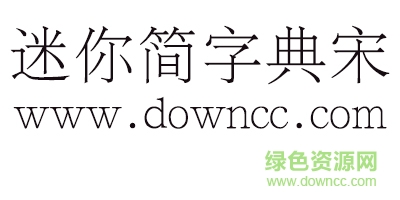
迷你簡字典宋字體是一款迷你字體設(shè)計方面的字體,能夠讓你的輸入法字體擁有超強(qiáng)的個性化。
宋體,是為適應(yīng)印刷術(shù)而出現(xiàn)的一種漢字字體。筆畫有粗細(xì)變化,而且一般是橫細(xì)豎粗,末端有裝飾部分(即「字腳」或「襯線」),點(diǎn)、撇、捺、鉤等筆畫有尖端,屬于襯線字體(serif),常用于書籍、雜志、報紙印刷的正文排版。
宋朝文化興盛,印刷業(yè)有了巨大發(fā)展,從南宋時期,在臨安等地的印刷作坊里就開始出現(xiàn)了類似印刷體的字體,后世稱之為仿宋體。明朝時期,文人追捧宋刻本書籍,于是刻匠們加粗仿宋體的豎線和筆畫的端點(diǎn)以抵抗刻版磨損,卻依舊稱之“宋體”。現(xiàn)代的所謂宋體基本上就是這樣成型的。